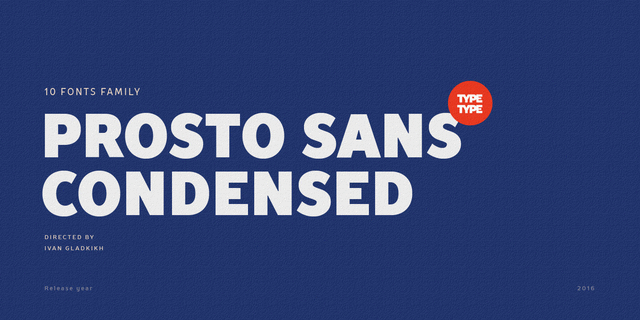
Prosto Sans Condensed – это компактная версия шрифта Prosto Sans. Вы можете использовать его практически везде. Каждый штрих этого шрифта эмоционально нейтрален. Это сделано для того, чтобы не отвлекать от восприятия текста и не искажать его смысл. Иметь Prosto Sans и Prosto Sans Condensed в вашей коллекции, все равно что иметь универсальный инструмент, помогающий ремонтировать что угодно в любой момент. Благодаря сжатым пропорциям ваш текст будет вмещаться в более компактное строки и полосы набора. Шрифт Разработан Иваном Гладких в студии TypeType в 2016 году.
минималистичный, четкий, деликатный, чистый, легкий, прохладный, свежий, модный, тонкий, современный, лаконичный, ясный, ровный, понятный, качественный, городской, логичный, точный, глобализированный, глобалистичный, интимный, хрупкий, проволочный, худой, простой, твердый, доступный, элементарный, правильный, строгий, серьезный, устойчивый, статичный, стабильный, самостоятельный, ответственный, западный, деловой, холодный, спокойный, комфортный, умный, удобный, безразличный, равнодушный, практичный, вежливый, значительный, обязательный, солидный, сильный, убедительный, важный, мотивирующий, надежный, тяжелый, урбанистический, грубый, заметный, яркий, активный, броский, тесный
парфюмерия, туалетная вода, шампунь, косметика, мода, город, инновации, парикмахерская, диета, дизайн, гигиена, чистота, общество, архитектура, наука, одежда, реклама, магазин, здоровье, медицина, лекарство, гаджет, Айтишник, IT, айтишник, айти, технологии, транспорт, аэропорт, метро, навигация, бизнес, торговля, конструктор, чертеж, деньги, банкнота, обувь, мобильная связь, монета, прибор, техника, зубная паста, футбол, спорт, автобус, инструмент, станок, урбанистика, топливо, энергетика, сталевар, мотор, двигатель Стилистика: